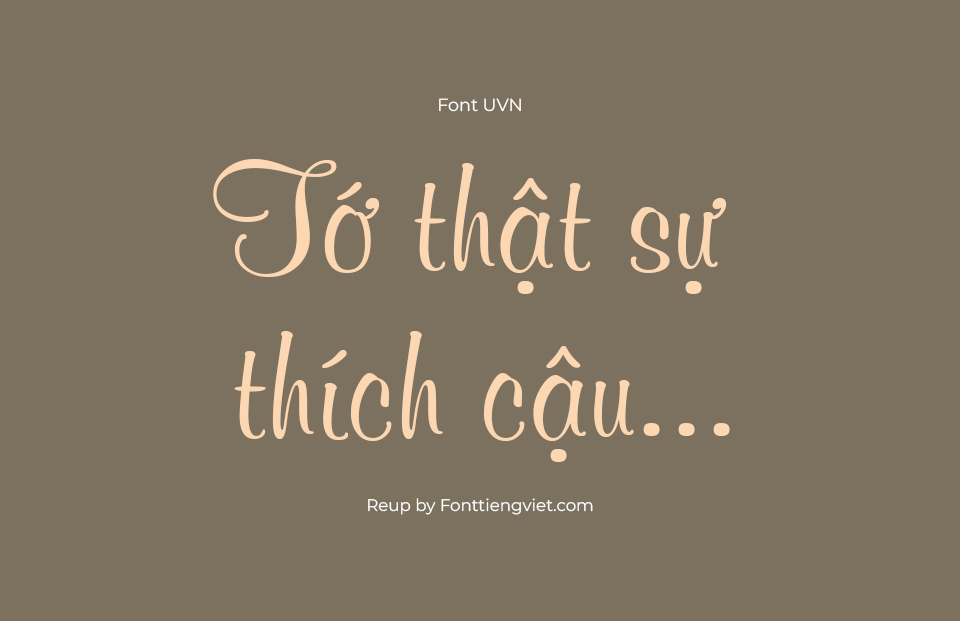
Font Việt Hóa UVN Moi Hong
Giới thiệu về bộ Font Việt Hóa UVN Moi Hong
Trong thế giới thiết kế đồ họa học đường, việc lựa chọn một Font Miễn Phí phù hợp là yếu tố quan trọng để tạo nên sự gần gũi. Font Việt Hóa UVN Moi Hong là một trong những kiểu chữ độc đáo thuộc bộ mã UVN, mang phong cách thanh mảnh nhưng không kém phần mềm mại. Với các đường nét mô phỏng nét vẽ thủ công, bộ font này cực kỳ phù hợp cho các bài giảng trình chiếu, trang trí báo tường hoặc làm thiệp chúc mừng. Điểm nổi bật nhất của font chữ này chính là tính ứng dụng cao trong môi trường giáo dục Việt Nam nhờ bảng mã Unicode chuẩn xác, giúp hiển thị tiếng Việt trọn vẹn mà không bị lỗi dấu.
Đặc điểm nổi bật của Font Việt Hóa UVN Moi Hong
Thiết kế tối ưu cho giáo dục
Font Việt Hóa UVN Moi Hong sở hữu những đường nét uốn lượn tự nhiên, gợi liên tưởng đến những cánh hoa đào hoặc nét vẽ nghệ thuật nhẹ nhàng. Điều này giúp các bạn học sinh dễ dàng sáng tạo các sản phẩm thủ công hay bài thuyết trình Powerpoint sinh động. Giáo viên có thể sử dụng font để làm tiêu đề bài học, giúp học sinh cảm thấy hứng thú hơn với nội dung trình bày.
Khả năng tương thích và định dạng